对于设计师而言,为每个设计选择合适的字体是必须掌握的知识要点。如果你正在为“怎样选择合适的字体和有效地使用字体”而感到困惑,那么今天这篇文章应该可以帮助到你。创意字体在普通字体的形象上增加了直观性、趣味性。整体更形象化,加强了字体的表现力却不影响字体的完整性,给人印象深刻。一起来看下小编下面的图片字体吧了解小编为大家推荐的创意字体吧!
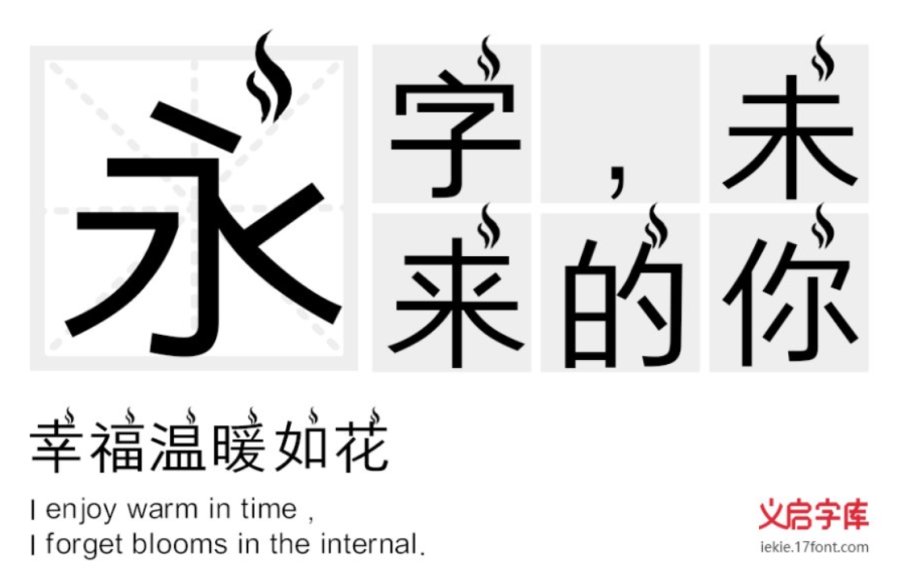
这款的字体的名字叫做“热的冒烟体”,被炎热的太阳晒得都开始冒烟了。字体的字形保留了字体原型的方正得体,诠释了独特的规整美并带有大气的商务感。设计师在这个基础上进行艺术创作,增添的字体的趣味感。
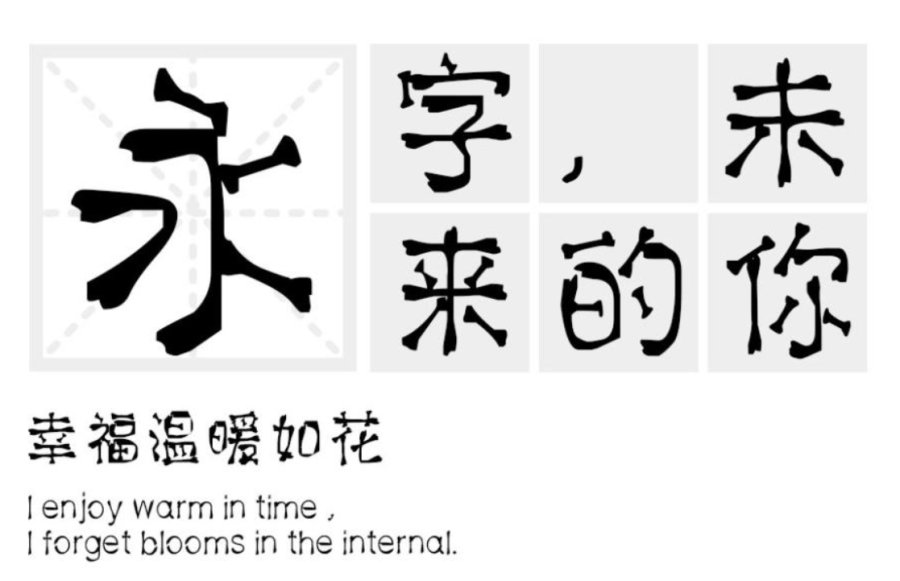
通常字形中的点、撇、捺、钩、提等笔画各具面目,而这款“汉标馋骨体”笔画运用了骨头图形元素来构建,把这些笔画做成了骨头,概括为飘逸的骨头,并且使左右舒展的笔画尽量对称,最大限度地简化笔画骨头造型。
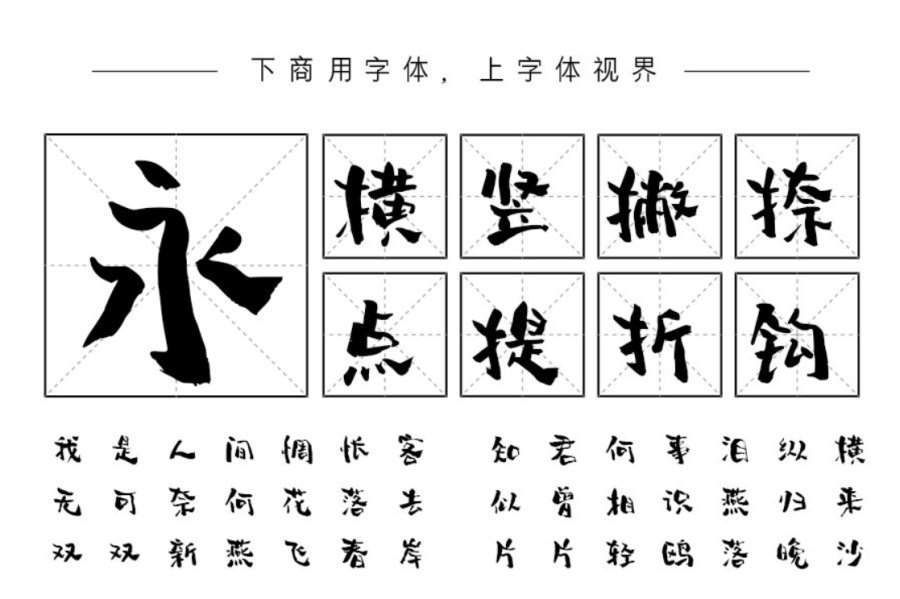
这款“站酷妙典和风体”基于传统书法字形结构基础上,用区别于传统毛笔书写运笔方式,使字形笔画结构具有轻松、趣味、笨拙、不拘一格的字体性格特点独特的笔法结构,使字体在商业创意设计中,适用于各种行业众多场景。